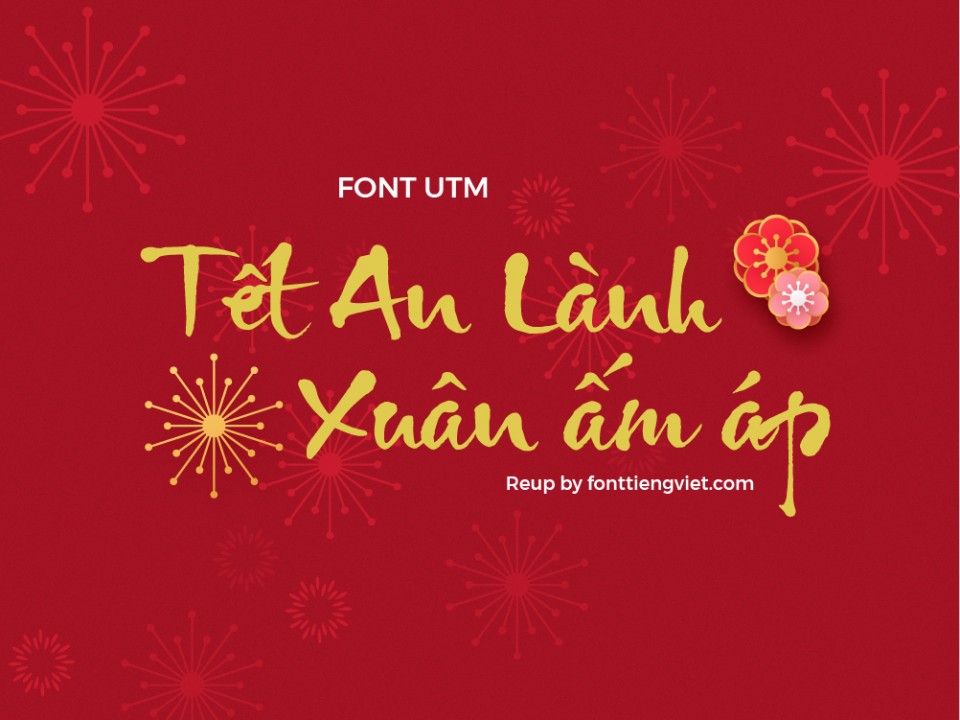
Font việt hóa UTM Ông Đồ Già – tết
Font việt hóa UTM Ông Đồ Già – tết: Nét chữ thư pháp cổ điển cho mùa xuân
Giới thiệu về Font việt hóa UTM Ông Đồ Già – tết
Trong không khí rộn ràng của những ngày cuối năm, việc tìm kiếm một bộ Font Miễn Phí mang đậm bản sắc văn hóa dân tộc là điều vô cùng cần thiết. Font việt hóa UTM Ông Đồ Già – tết chính là lựa chọn hoàn hảo để tái hiện hình ảnh cụ đồ già bên nghiên bút, giấy đỏ. Đây là bộ font được thiết kế dựa trên phong cách thư pháp uyển chuyển, giúp các thiết kế trở nên gần gũi và ấm cúng hơn trong dịp Tết nguyên đán.
Đặc điểm nổi bật của Font việt hóa UTM Ông Đồ Già – tết
Bộ phông chữ này sở hữu những đường nét thanh đậm rõ rệt, mô phỏng chân thực từng nhát cọ vẽ trên giấy điệp. Với ưu điểm đã được việt hóa hoàn chỉnh, người dùng có thể dễ dàng gõ tiếng Việt có dấu mà không lo lỗi font hay mất ký tự. Sự kết hợp giữa tính truyền thống và công nghệ kỹ thuật số giúp các bạn học sinh dễ dàng tiếp cận nghệ thuật thư pháp xưa ngay trên máy tính của mình.
Ứng dụng thực tế của phông chữ trong giáo dục và đời sống
Thiết kế thiệp chúc mừng và báo tường
Việc sử dụng Font việt hóa UTM Ông Đồ Già – tết trong các hoạt động ngoại khóa như làm báo tường hay thiết kế thiệp chúc mừng giúp học sinh hiểu thêm về nét đẹp văn hóa truyền thống. Những câu đối đỏ hay lời chúc đầu năm sẽ trở nên trang trọng, ý nghĩa hơn khi được trình bày bằng kiểu chữ thư pháp đặc trưng này.
Trang trí không gian lớp học ngày Tết
Thầy cô và các em có thể dùng font chữ này để in ấn các biển hiệu, bảng tin hoặc banner chào đón mùa xuân. Sự mềm mại của từng nét chữ giúp tạo nên không gian học tập thân thiện, mang đậm tinh thần ngày Tết cổ truyền Việt Nam.
Kết luận về bộ font chữ thư pháp ý nghĩa